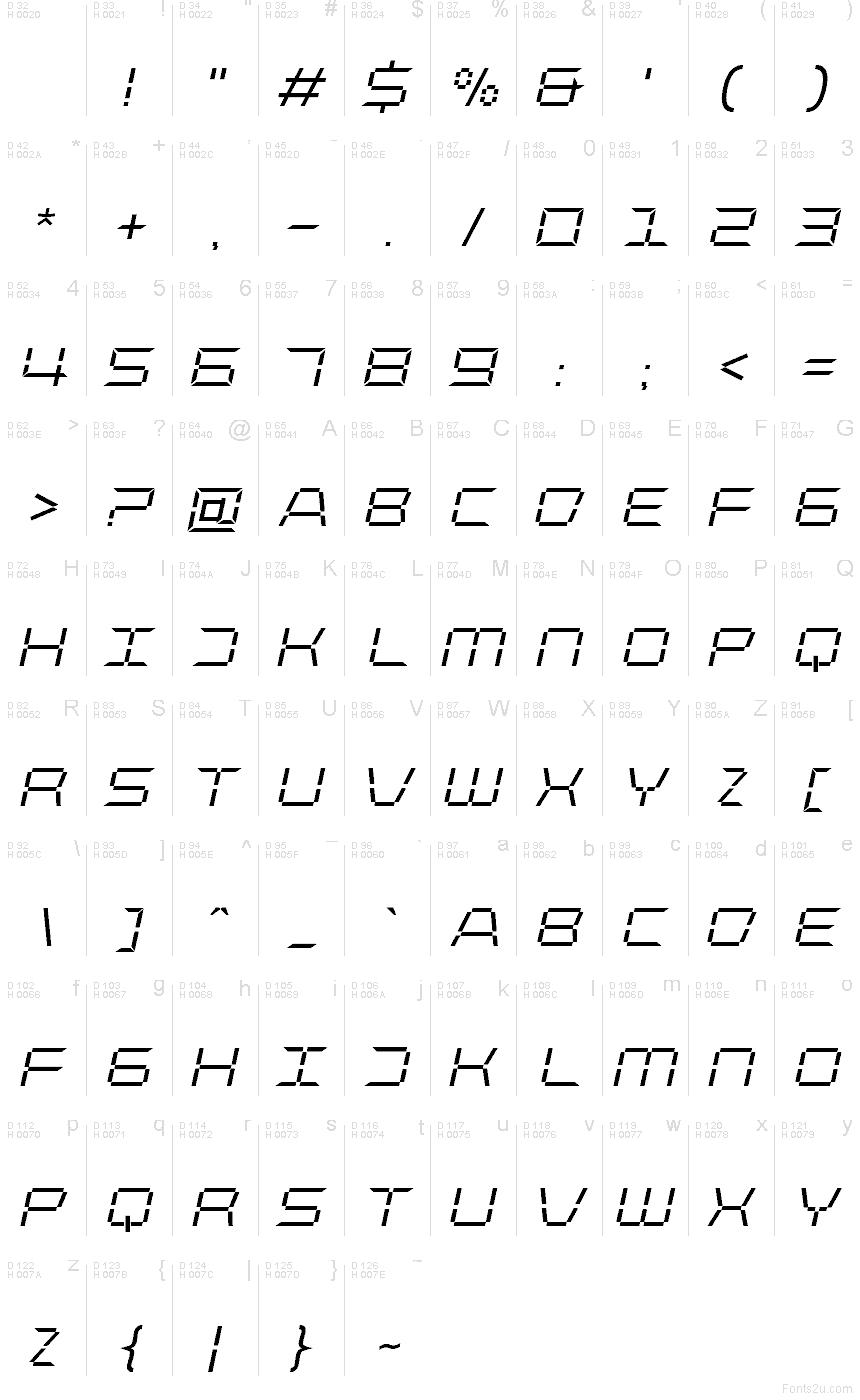
Digitrone Bold Italic od Fikryal Studio je bezplatné hranaté digitální display písmo, které vychází ze segmentových elektronických nápisů. Je roztažené do velmi širokých proporcí s výrazným sklonem dopředu a záměrnými otevřenými mezerami v mnoha spojích. Jeho dlouhé horizontální linie a seříznuté spoje působí zřetelně mechanickým dojmem.
Technologická značka by toto písmo mohla uplatnit na obalech produktů, v grafice rozhraní i ve vizuálech pro akce a využít jeho preciznost přístrojové desky k vyjádření rychlosti, technického výkonu a elektronického řízení. Tytéž výrazné formy se hodí také pro názvy sci-fi her a reklamní předměty pro motorsport, protože ostrý styl tachometru oslovuje mladší publikum inklinující k retrofuturistickému hardwaru a vizuální kultuře arkádové éry.